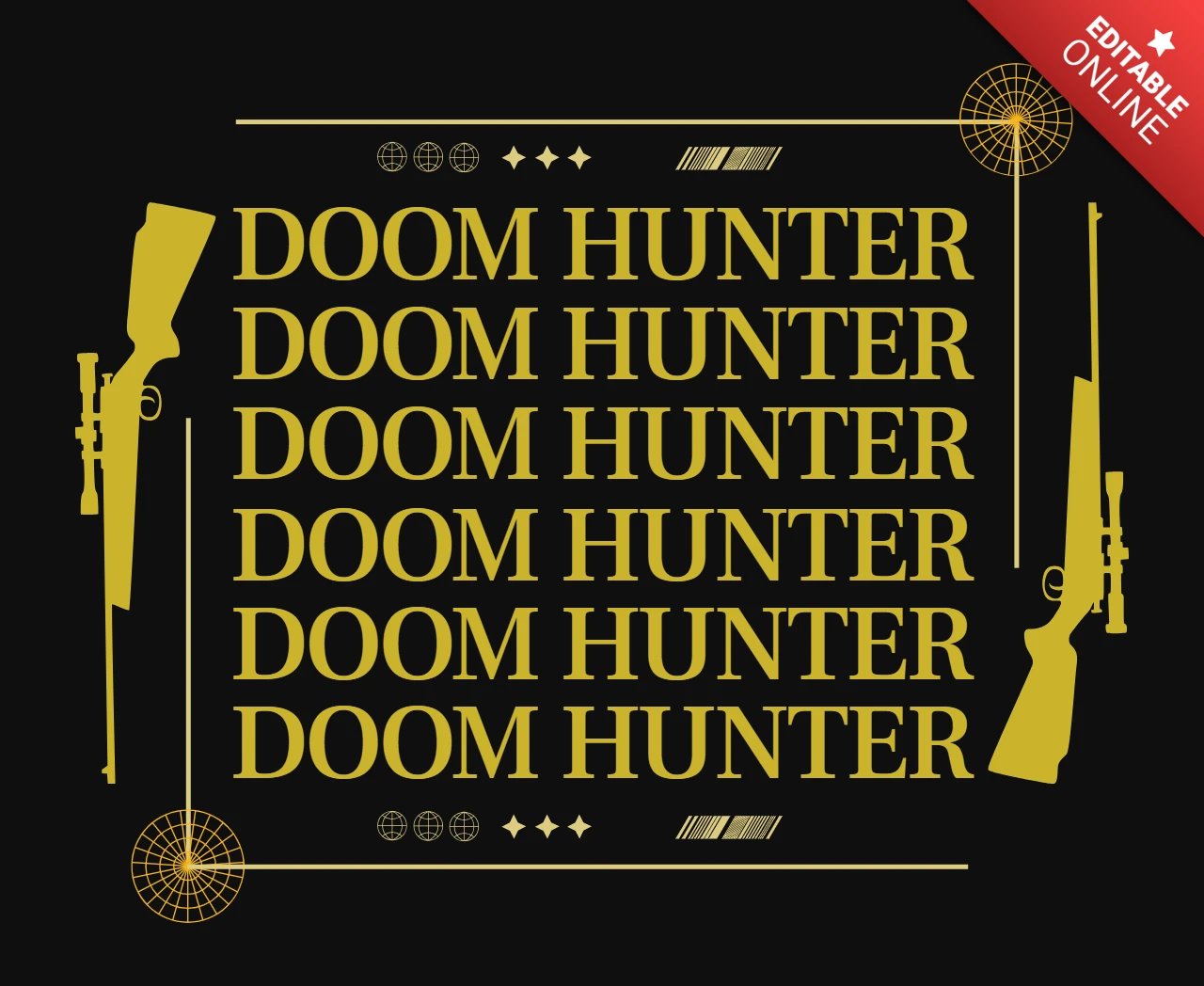
Template de typographie en gras avec des fusils pour la conception de marchandises de jeux vidéo
Éditer dans Design Studio Télécharger en JPGLibérez votre créativité avec nos modèles de design modernes, présentant une typographie audacieuse et des éléments abstraits, parfaits pour les produits dérivés de jeux, les vêtements de rue et les œuvres murales accrocheuses.